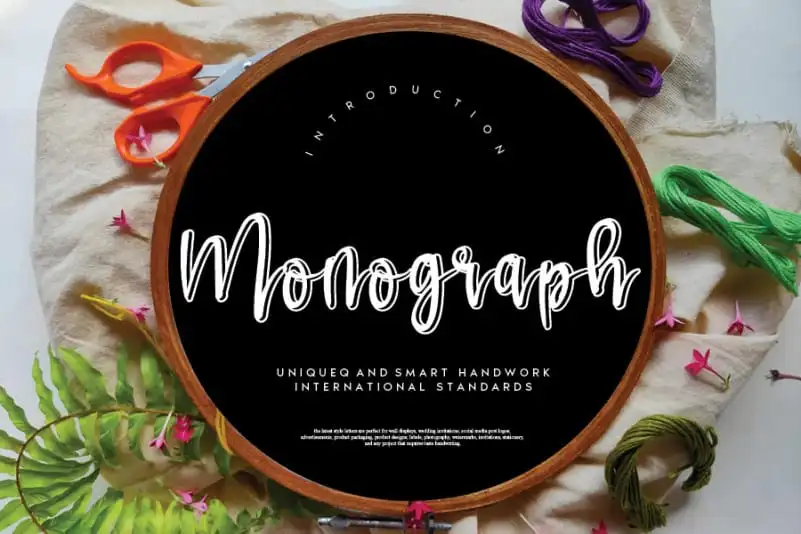
Monograph Script Font é uma elegante fonte escrita à mão que flui com fluidez, projetada para encantar seus melhores trabalhos. Suas características distintivas e sua alma eterna a tornam perfeita para criar designs impressionantes. Esta fonte foi criada pelo designer andikastudio, oferecendo uma experiência única e inspiradora para quem busca um toque único em suas criações digitais. Engajante e versátil, Monograph Script Font é o tipo de fonte à mão que você pode querer adicionar a sua galeria de recursos gráficos. Adquira-a hoje e transforme as mais simples ideias em obras de arte perfeitas.